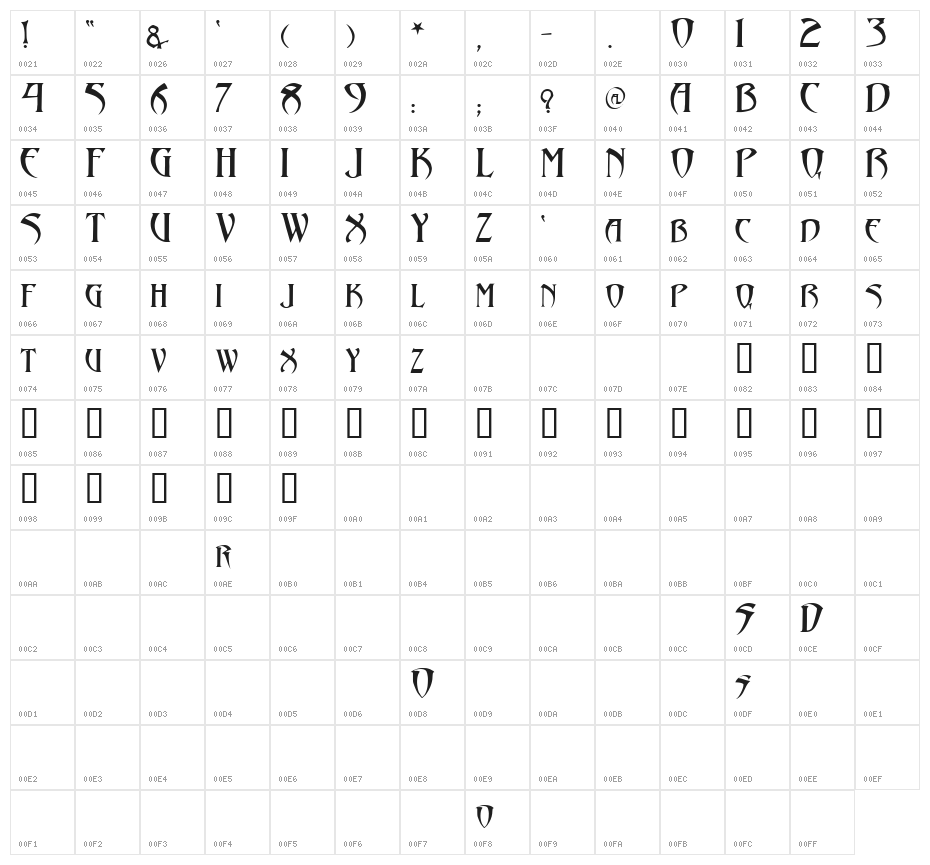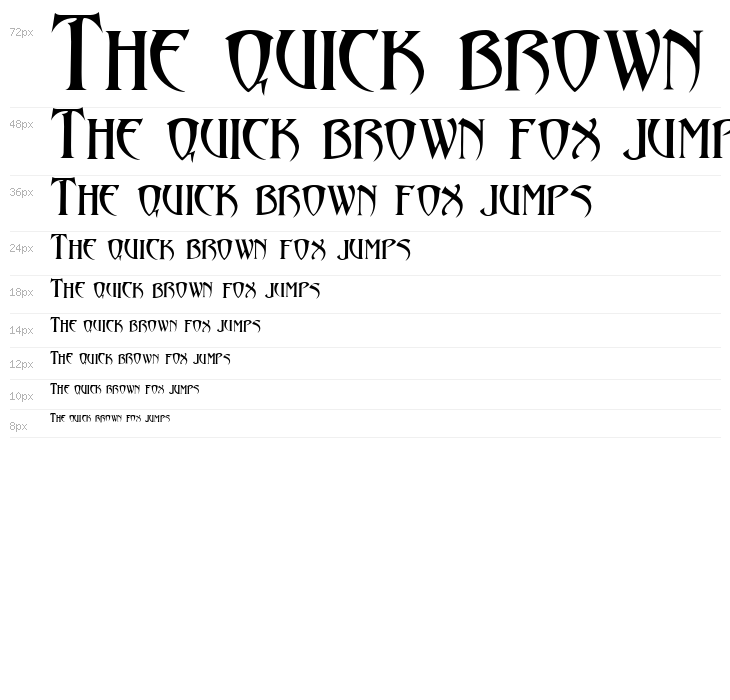
Arthur Gothic Font
| Anwendungsfall | Logos, Headlines, Posters |
| Vorgeschlagene Projekte | Ideal for use in fantasy-themed designs, book covers, posters, and branding that requires a dramatic and medieval touch. |